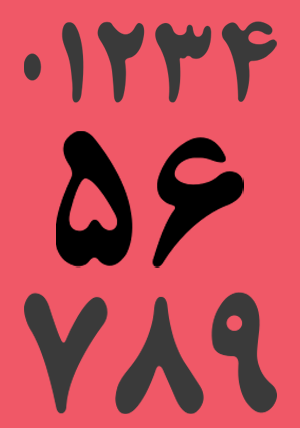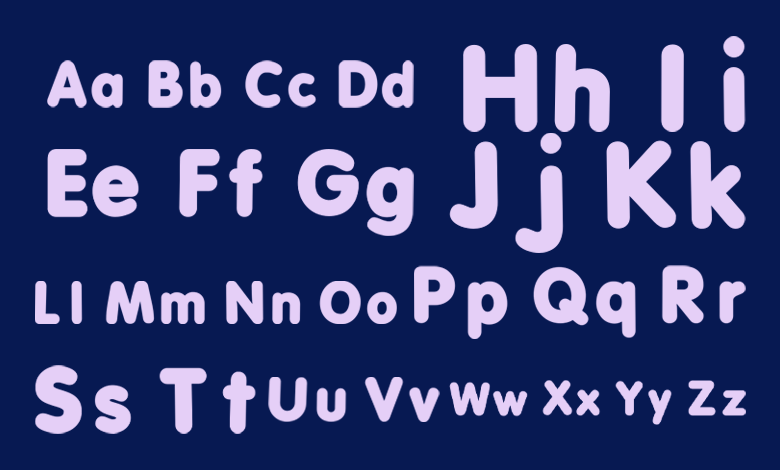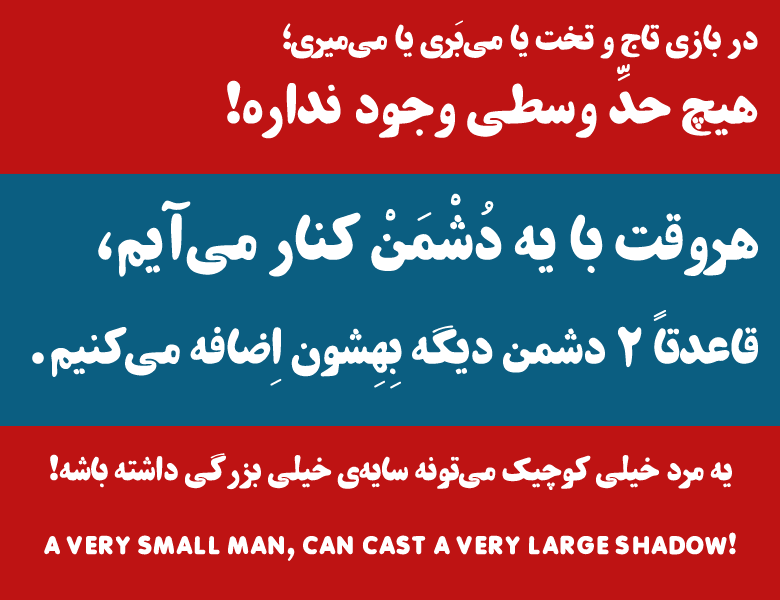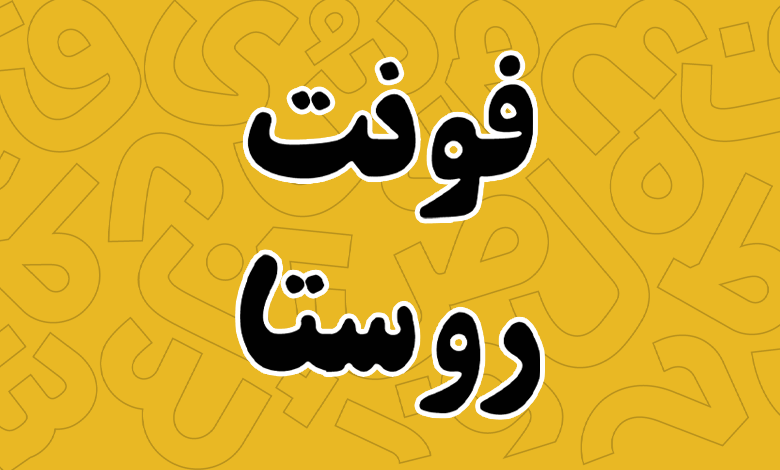
فونت روستا (Roosta)
فونت روستا رایگان (Roosta) یک قلم در سبک تیتر و با ظاهری فانتزی است که میتوان از آن برای موضوعاتی که جنبه عمومی داشته و با زندگی روزمره مردم سر و کار دارد استفاده کرد. این فونت توسط زهرا روستا طراحی شده و به صورت کاملا رایگان جهت استفاده در دسترس است.
طراحی فونت روستا به صورت کاملا آزاد و با دست انجام شده تا حس و حال عامیانه و کودکانه خود را حفظ کند. یکی از بیشترین کاربردهایی که این فونت دارد در صنعت چاپ است که برای تهیه کتاب کودک مصور از آن استفاده میشود. از این فونت میتوان برای جلد کتب، داستانهایی با تصاویر خلاقانه و طنز استفاده کرد.
در ادامه این نوشته از سایت فونتچی به نقد و بررسی کامل فونت روستا خواهیم پرداخت؛ فونتی که در ظاهر یک فونت دستنویس بهنظر میرسد اما درواقع یک فونت تیتر و مناسب برای استفاده در عناوین و متنهای نسبتا بلند است که بیشتر با صنعت چاپ، بهویژه در حوزه کودک و نوجوان کاربردی است.
فونت زهرا روستا برای زمانی که نیاز به یک ساختار فونت فارسی ایرانی مناسب برای تیتر دارید انتخاب خوبی خواهد بود. این فونت خارج از چارچوب ماشینی و هندسی فونت قرار دارد و با ساختاری صمیمی و عامیانه که دارد، میتواند ارتباط نزدیکی را با مخاطب برقرار کند.
از همین رو بهترین استفاده از این فونت در کتب کودک و نوجوان یا محتواهایی با درون مایه طنز است که روی انتقال حس مناسب نیز تاثیرگذار است.
استایل و وزن فونت روستا
پشتیبانی از زبان انگلیسی و عربی
فونت روستا فارسی از سایر زبانها نیز پشتیبانی میکند. این فونت برای زبان انگلیسی همان ساختار دوستانه و گرم پیادهسازی شده را برای حروف لاتین دارد با این تفاوت که بر خلاف نسخه حروف فارسی که پهنای فونت در بخشی از حروف چاق و بخشی دیگر لاغر است، در نسخه انگلیسی از پهنای ثابتی پشتیبانی میکند.
شاید ایرادی که بتوان به این فونت گرفت این باشد که نسخه انگلیسی فاقد اعداد لاتین است و با تایپ اعداد چه در حالت لاتین و چه فارسی، در هر صورت اعداد فارسی تایپ میشوند. بنابراین برای متون انگلیسی نیاز به استفاده از فونت دیگری که نزدیک به این فونت باشد دارید.
زبان دیگری که فونت روستا از آن پشتیبانی میکند عربی است. پشتیبانی در زبان عربی باتوجه به اینکه از رسمخط فارسی بهره میبرد کامل است و شامل اعراب میشود. اعراب در تمامی حروف نیز همان سبک نگارش و پهنای در نظر گرفته شده برای حروف را دارند.
اما برای زبان عربی نیز یک ایراد جزئی در همان بخش اعداد وجود دارد و نمیتوانید اعداد عربی «٤٥٦» که ساختاری متفاوت با اعداد فارسی دارند را به این سبک فونت تایپ کنید و اعداد عربی نیز کاملا با ساختار اعداد فارسی تایپ میشوند.
مناسب برای صنعت چاپ و کتب کودک
از فونت زهرا روستا میتوانید در صنعت چاپ استفاده کنید. حال چه استفاده برای چاپ کتاب و مطبوعات باشد، چه از آن برای تبلیغ محصولات استفاده کنید.
برای استفاده از این فونت با هدف تبلیغات توصیه میشود که در محصولاتی که مربوط به همان حوزه کودک و نوجوان هستند استفاده گردد. چرا که همان حس و حال صمیمی را انتقال داده و میتواند روی جلب توجه موثر باشد.
این فونت فاقد گلیف اختصاصی برای کاراکترهای خاص هست.